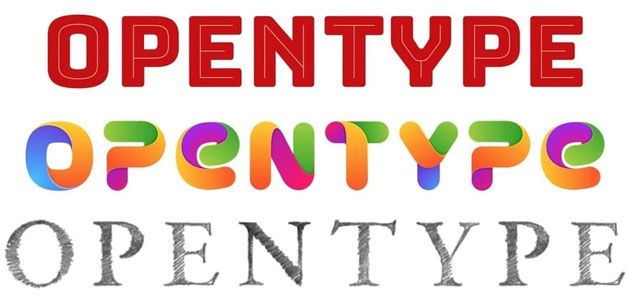
Color fonts (цветные шрифты) OpenType-SVG — это новый тренд в веб-дизайне, или как выражаются буржуи — The next big thing.
Что это за технология такая, когда она успела стать трендом и почему у нее большое и светлое будущее?
Как вы и сами прекрасно знаете, в Интернете шрифты имеют только один заданный цвет. Шрифт может быть синим или красным, но не может быть одновременно красно-синим.
В прошлом разработчики экспериментировали с разноцветными шрифтами, но безуспешно. Пока не появились emoji, ставшие частью Unicode. Смайлики, летающий бизнесмен и кучка сами знаете чего сразу же заполонили весь Интернет.
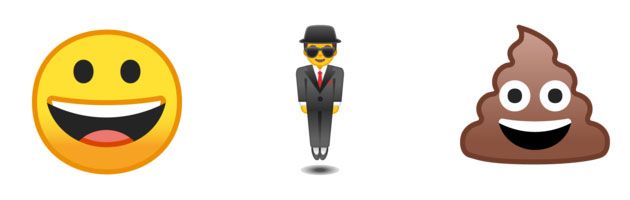
Следом за emoji появилась технология раскрашивания шрифтов в формате OpenType-SVG. Формат шрифта OpenType-SVG был первоначально разработан Mozilla & Adobe и стал отраслевым стандартом в начале 2016 года.
По сути, файл цветного шрифта — это обычный файл шрифта, который содержит дополнительные данные, чтобы отображать больше графических свойств. Он содержит векторные фигуры с цветом или градиентами, а также может включать растровые изображения.
Разумеется, это делает шрифт OpenType-SVG гораздо тяжелее обычного шрифта, но нам ли печалиться? При современных возможностях и скоростях Интернета такими вещами можно легко пренебречь. А если хотите чтобы программы Adobe работали с цветными шрифтами на вашем компьютере быстрее, то графическая станция станет хорошим подспорьем.
Сегодня существуют четыре основных формата цветных шрифтов, которые вписываются в обычные файлы шрифтов: SBIX, COLR, CBDT и SVG. Каждый из них имеет свои особенности. Из-за различий и несовместимости этих форматов индустрии дизайна придется пройти через переходный период для обеспечения кросс-платформенной совместимости в различных операционных системах, браузерах и приложениях.
Кроме того, у цветных шрифтов есть та же проблема, что и у обычных растровых изображений. Если цветные шрифты, основанные на векторных глифах, масштабируются без потерь качества, то шрифты на основе растровых изображений будут терять в качестве при увеличении. То есть, все как с обычными картинками в фотошопе.
Таким образом, веб-дизайнерам потребуется несколько версий файлов шрифтов с полноразмерными растровыми изображениями, что еще больше увеличит их общий вес.
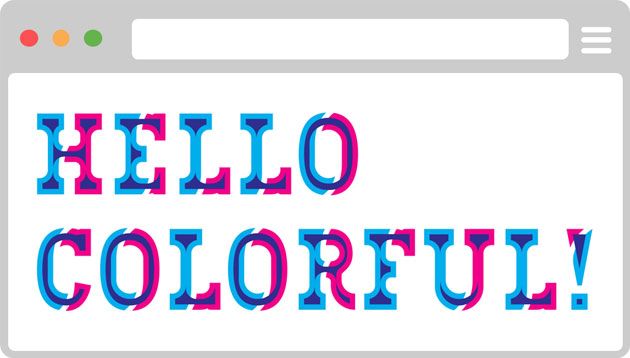
Где и как применять цветные шрифты, я уверена, вы придумаете сами. Например, из них замечательно получаются заголовки и названия сайтов. Если раньше приходилось отрисовывать их в фотошопе и добавлять на сайт в качестве обычной картинки, снабжая обязательным атрибутом alt, то теперь можно не морочиться и сделать это при помощи полноценного шрифта.
Предприимчивые создатели шрифтов уже постарались и выпустили ряд цветных шрифтов. Вы можете скачать их и использовать в своих проектах. Это такие цветные шрифты как Fontself, Type with Pride, Beach Towel, Bungee, Watercolor Font, и др. Подробнее читайте здесь и здесь (англ).